蒙纳首届TCA字体大赛结果公布
赢家们来了!
前天,蒙纳公司(Monotype)公布了新成立的奖项Type Champions Award的首届获奖名单。中国的阿里巴巴公司成为了亚洲地区唯一的获奖者。
蒙纳是一家为众多品牌提供字形建造、授权和设计的公司。根据蒙纳官方网站说明,Type Champions Award旨在表彰那些在设计和字体方面追求卓越的品牌。这些品牌在延展和维护品牌形象的同时,开创并使用了兼具创新性且令人印象深刻的字体设计。
获奖者
近年来,众多主流消费品牌已经将品牌定制字体视为市场营销工作的重要环节,从本届获奖者可以看出,那些获奖的品牌所共同具备的特质包括:重视真诚地传达品牌/创意信息、给客户带来与品牌调性一致的体验、通过选择字体设计让品牌更经得住时间的考验、在营销和广告上进行创意策略(使用新兴的渠道、吸引新/现有客户的独特战略、一系列创意字体),以及在字体设计和创意上作出关键性的努力。
在Type Champions Award的提名过程中,蒙纳还请了多位创意专业人士和专家小组来分析确认现在和未来会推动设计的最流行趋势,并推出了一本关于字体设计趋势的全新线上手册,这通常是之各大品牌战略广泛转变的一个重要指标。(可在官网注册下载,链接:https://hello.monotype.com/5-Type-Trends-for-Brands-2020.html )
根据这份可下载的报告,“2020年的5大字体设计趋势”如下:
1. 全球语言覆盖的必要性
2. 可变字体的兴起
3.强调对称的无衬线字体
4.作为标识的字体:装饰性元素的复兴
5. 永远在重塑品牌
Design360°为大家整理了赢得今年Type Champoions Award的的12个品牌,来看看他们的视觉形象标识和字体设计。
阿里巴巴 Alibaba Group
"Fit for a passionate, powerful and future-forward brand."
阿里巴巴在今年4月发布了一款新字体“阿里巴巴普惠体”,这是一款由中国企业首次发布的可面向全场景使用的免费商用正文字体。其西文部分由蒙纳的小林章设计,共收录116,895个全形汉字(含5个字重),西文Alibaba Sans共7205个拉丁字母(2种风格,11个字重),覆盖172个语种,可以满足阿里巴巴集团及其经济体公司在全球化业务下的多个应用场景需求。
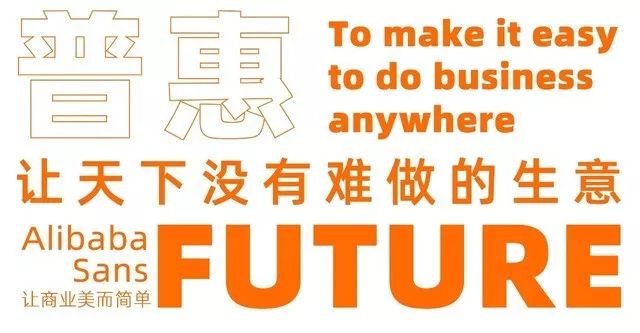
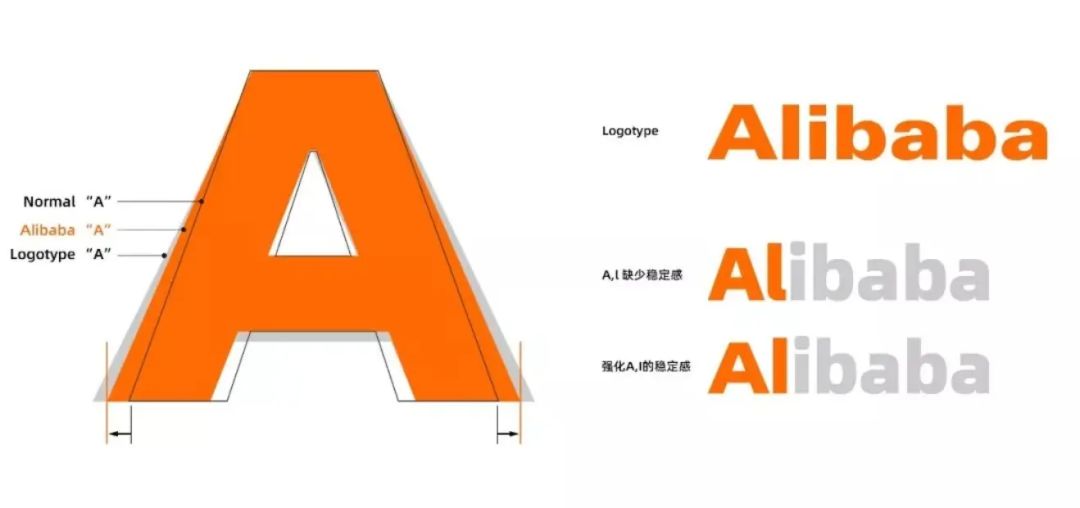
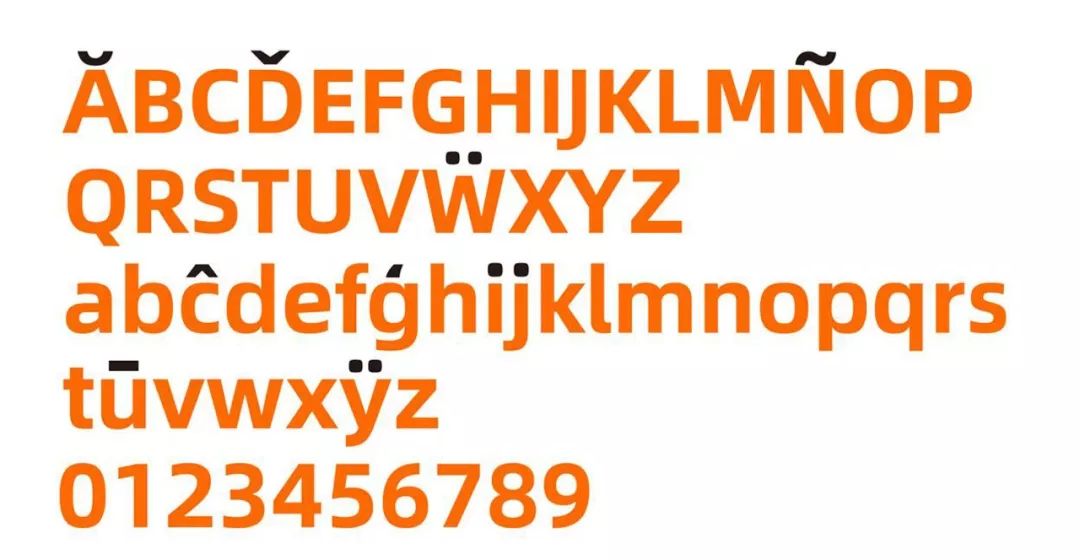
奥迪 Audi
"A flexible type system is at the heart of the Audi brand identity."
2017年,德国汽车品牌奥迪(Audi)推出了自2009年来最大幅度调整的扁平化新标志和新的品牌定制字体Lorem,伦敦的Sawdust设计工作室还专门给奥迪的专属杂志设计了一系列特别的展示字体。奥迪是德国历史最悠久的汽车制造商之一。从1932年起,奥迪便开始采用四环徽标,这次把商标扁平化的举动一方面呼应了未来互联网运作的方式,一方面是表明品牌将以更简约的美学向未来迈进。
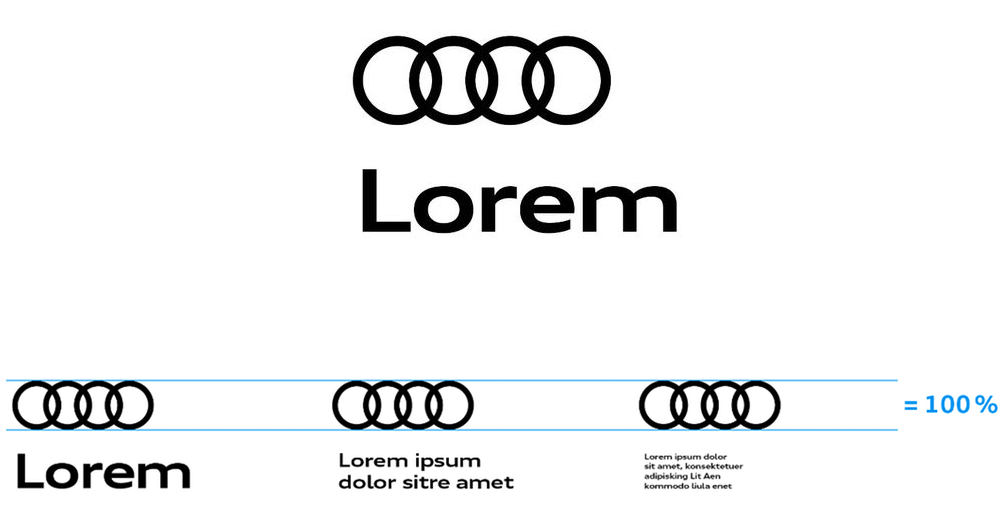
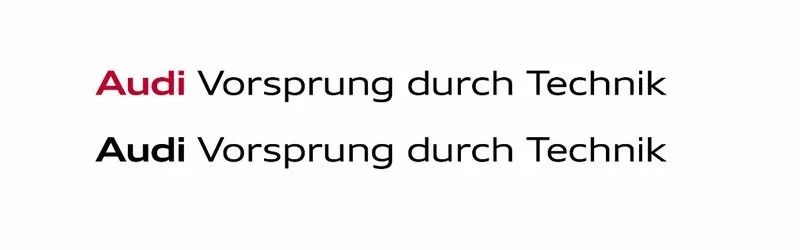
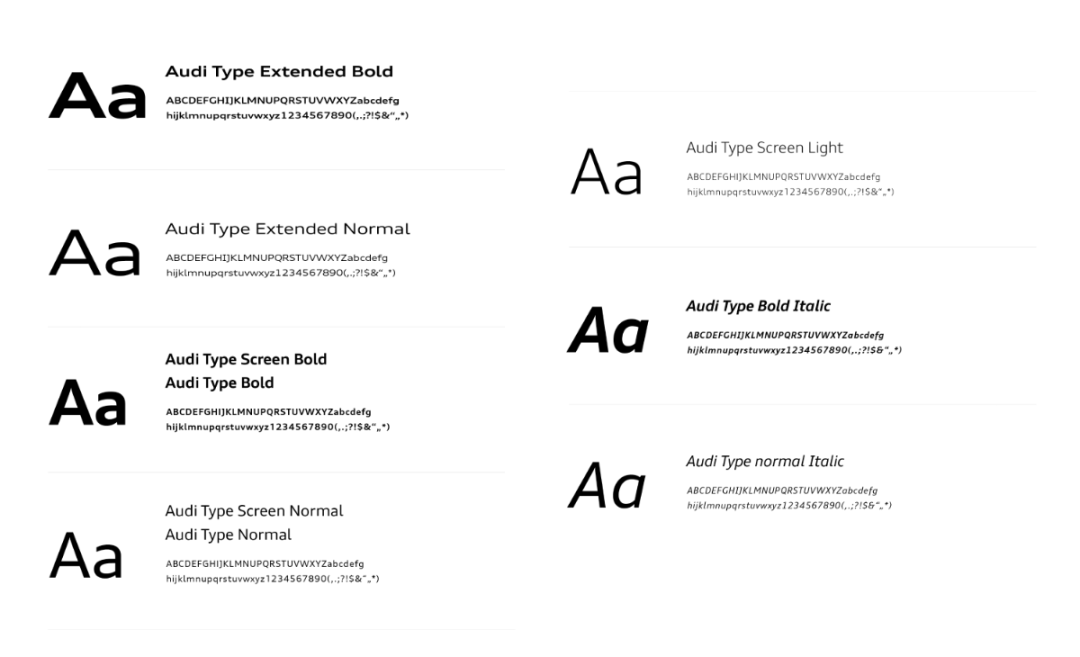
Dropbox
"A new identity that embodies the brand's playfulness at every touchpoint."
自07年创立以来,云存储服务商Dropbox在2017年第一次更新了品牌形象,包括一个全新的标识、一套色彩组合、一套包括259种不同字符的Sharp Grotesk字体以及一系列插画。
尤文图斯 Juventus
"A universal symbol of perseverance, ambition, and premium Italian style."
1897年成立的尤文图斯足球俱乐部(Juventus Football Club S.P.A)在2017年也迎来了巨大的视觉形象变化,由米兰设计工作室Interbrand为其设计了新的品牌标识和字体。尤文图斯足球俱乐部是意大利历史最为悠久的足球俱乐部之一,也是夺得意大利足球甲级联赛冠军最多的球队。虽然俱乐部意图通过新徽标迎来新时代,但队徽发布时有不少尤文的死忠粉丝批评新的队徽丢失了球队的传统。
黑猩猩邮件 Mailchimp
"Consistent and grounded, yet playful and expressive."
2018年,知名电子邮件营销服务平台黑猩猩邮件(Mailchimp)邀请Collins设计公司帮助他们重塑品牌形象,以反映和推动他们持续的业务转型。此次设计对品牌的标志大猩猩Freddie进行了简化,并推出了全新的品牌字体Cooper。Cooper是一种非常个性和具有开放性的字体。黑猩猩邮件创立于2001年,作为全球最大的营销平台之一,不仅提供电子邮件服务,还为各种规模的企业提供强大而先进的营销工具。
奥美 Ogilvy
"Oglivy has renewed its emphasis on craft across the full brand identity, with type at the forefront."
2018年,奥美公司(Ogilvy)与Collins设计公司合作,共同为奥美创造了全新的外观和字体系统,帮助品牌的重塑和推出。新的奥美标志代表了该品牌能够为其客户提供的敏捷性,协作性和连通性。奥美字体被重新定制为Ogilvy Serif和Ogilvy Sans,新标志字体参考了其创始人大卫·奥格威最喜欢的字体Baskerville。奥美是源自美国的跨国广告、市场营销及公关公司,目前为WPP集团旗下子公司,总部位于纽约。
西南航空公司 Southwest Airlines
"A contemporary brand persona, across the full customer experience."
2014年,西南航空公司(Southwest Airlines)推出了新涂装“Heart”、新LOGO以及新的字体系统Ubuntu,这是自2001年以来该航空公司首次推出新的涂装体系。此次视觉标识升级中,西南航空不再使用全部大写的Helvetica字体,转而采用笔画更粗、可以按客户要求进行改变的字体。与此同时,它还把部分字母转为小写,以传递一种更温和、友善的感觉。
Squarespace
"A Squarespace is uniquely positioned to expand the value of type to millions of creator sites worldwide."
Squarespace是纽约市的科技公司之一。DIA工作室与字体设计师Francois Rappo和Optimo字厂合作,为品牌创造了一种全新的字体Clarkson,它是纽约市城市交通系统中出现的Grotesk和Neo-Grotesk字体的混搭,并通过切割字形改变了字体重心来体现自己的独特性。Squarespace是一个由网站创建工具、网页托管服务及博客平台所组成,并以软件即服务模式运作的网上内容管理系统。该服务让个人或公司创建及修改网站及博客。
《卫报》The Guardian
"An eye-catching, purposeful, and type-driven visual identity."
英国《卫报》(The Guardian)在2018年改版,将其印刷尺寸改为小报尺寸,并随着报纸尺寸变化推出了一个新的网页、版头和标题字体。新字体Guardian Headline由内部设计团队与Commercial Type工作室合作完成。这个简洁、自信和富有冲击力的标题字体配合着色彩和图像,更能支持和加强卫报新闻的传达性。《卫报》创立于1821年,这家英国报纸发行量约为146,000份,网络用户每年的访问量达1.52亿人。
新学院 The New School
"An identity grounded in a technologically-sophisticated typeface: Neue."
2015年,Pentagram设计公司给新学院(The New School)更新了整体视觉形象,并为其制作了品牌专属字体Neue。新的标识和字体设计呼应了学院建筑和纽约市的风格特质,该字体系统既能展现学院本身的独立形象,同时能和其他学院联结起来。新学院成立于1919年,它是一所位于纽约市的美国高等教育机构,著名的纽约视觉艺术学院就是新学院旗下的学校之一。
& Other Stories
"A refreshing paired back and honest approach to fast fashion."
& Other Stories是H&M母公司海恩斯莫里斯公司 (Hennes & Mauritz AB) 旗下的高端女装品牌,创建于2012年。& Other Stories的名字和视觉标识的灵感来自于经常出现在故事集封面上的短语。
《纽约时报》The New York Times
"A legacy of relevance, sophistication, and a future-forward brand identity."
2015年,《纽约时报》(The New York Times)公布了最新的品牌标识设计,字体设计师Matthew Carter表示,新的LOGO设计意在表现“更现代、更优雅的空间感”。整套出版字体由A2-TYPE字厂的设计师Henrik Kubel设计,此次字体设计改版的整套流程由设计总监Gail Bichler以及艺术总监Matt Willey共同指导,由设计师Anton Ioukhnovets执行。《纽约时报》是一家美国日报,由纽约时报公司于1851年9月18日在美国纽约创办和持续出版。
2018年《纽约时报》发表的一篇关于品牌字体的文章中写道:“字体对公司营销越来越重要了,这是一种新沟通方式。字体的样式、大小、形状、粗细、颜色和深度都会说话,并且能够表达语气。正确地使用字体可以帮助品牌在竞争激烈的市场中脱颖而出。品牌需要知道哪些是它们的目标受众,需要表达哪些内容。”
可以确定的是,蒙纳创立的Type Champions Award将会继续见证并鼓励更多的品牌加入在创意策略上重视字体设计的阵营。